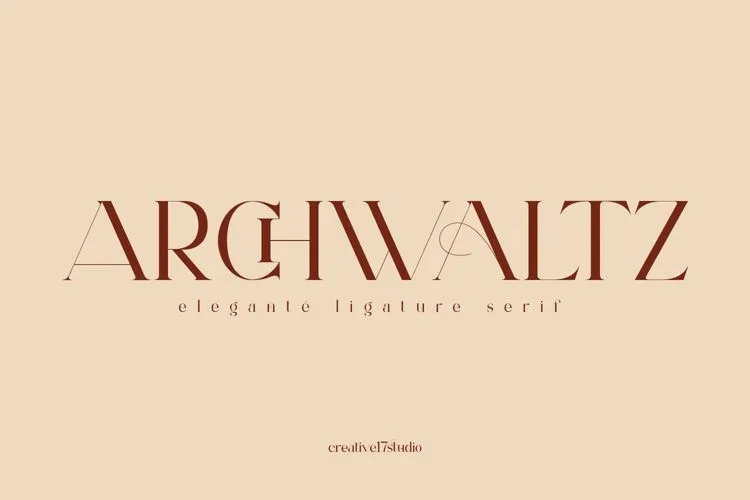
Archwaltz Serif Font – Download Grátis
A Archwaltz Serif Font é uma elegante fóntica serifada criada por Irfan Hidayat que mescla alegria com sofisticação. Desenvolvida para aqueles que prezam tanto pela modernidade quanto pelo toque tradicional, esta fonte se destaca por sua personalidade única e seu ar de luxo. Com muitos ligamentos elegantes, você sentirá prazer em usar essa fonte em seus projetos, garantindo um tom sofisticado sem perder a graça e o entusiasmo que ela traz. Engajada para designers que buscam uma fonte não apenas versátil e moderna, mas também com um charme especial que fazem dela uma escolha irresistível.